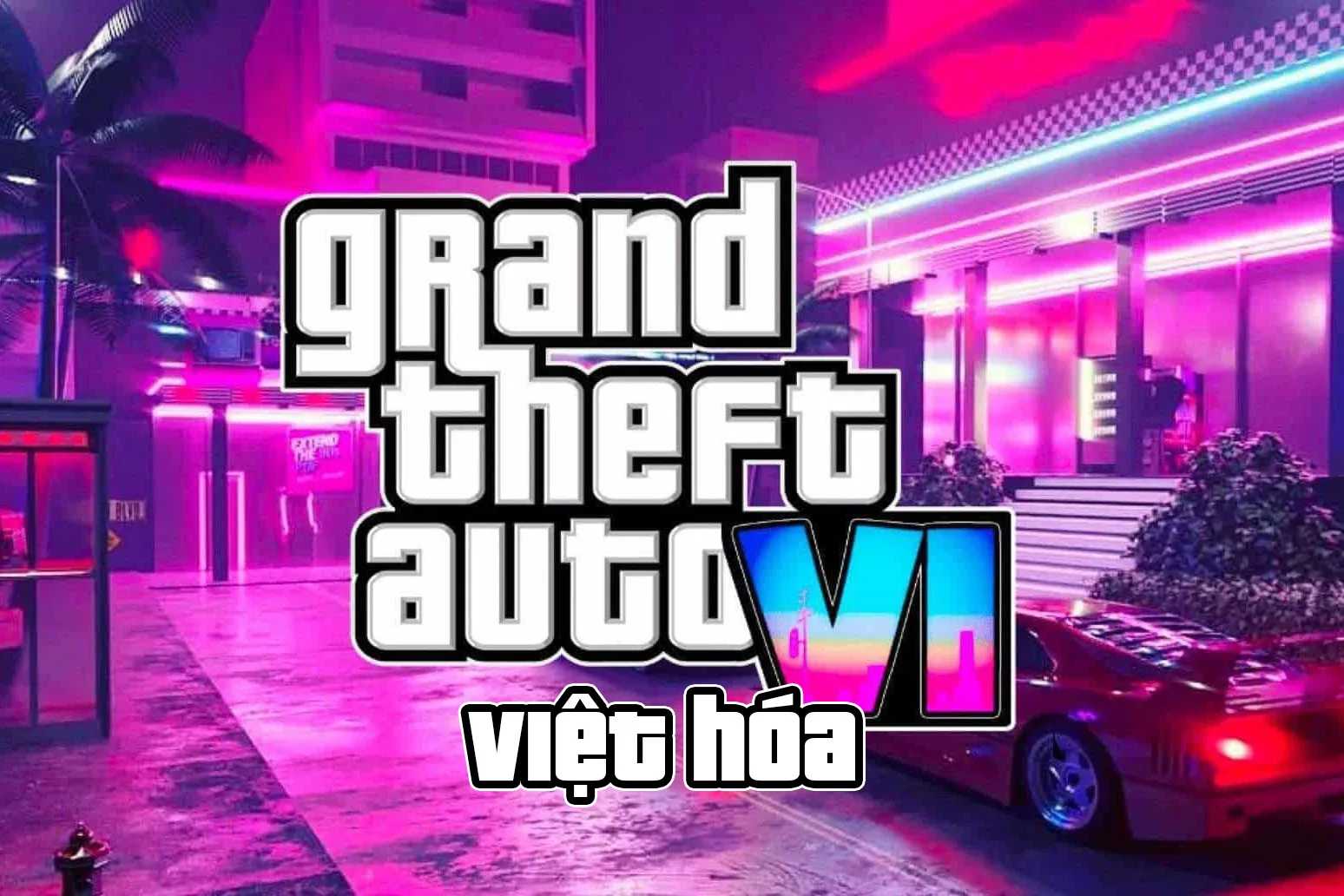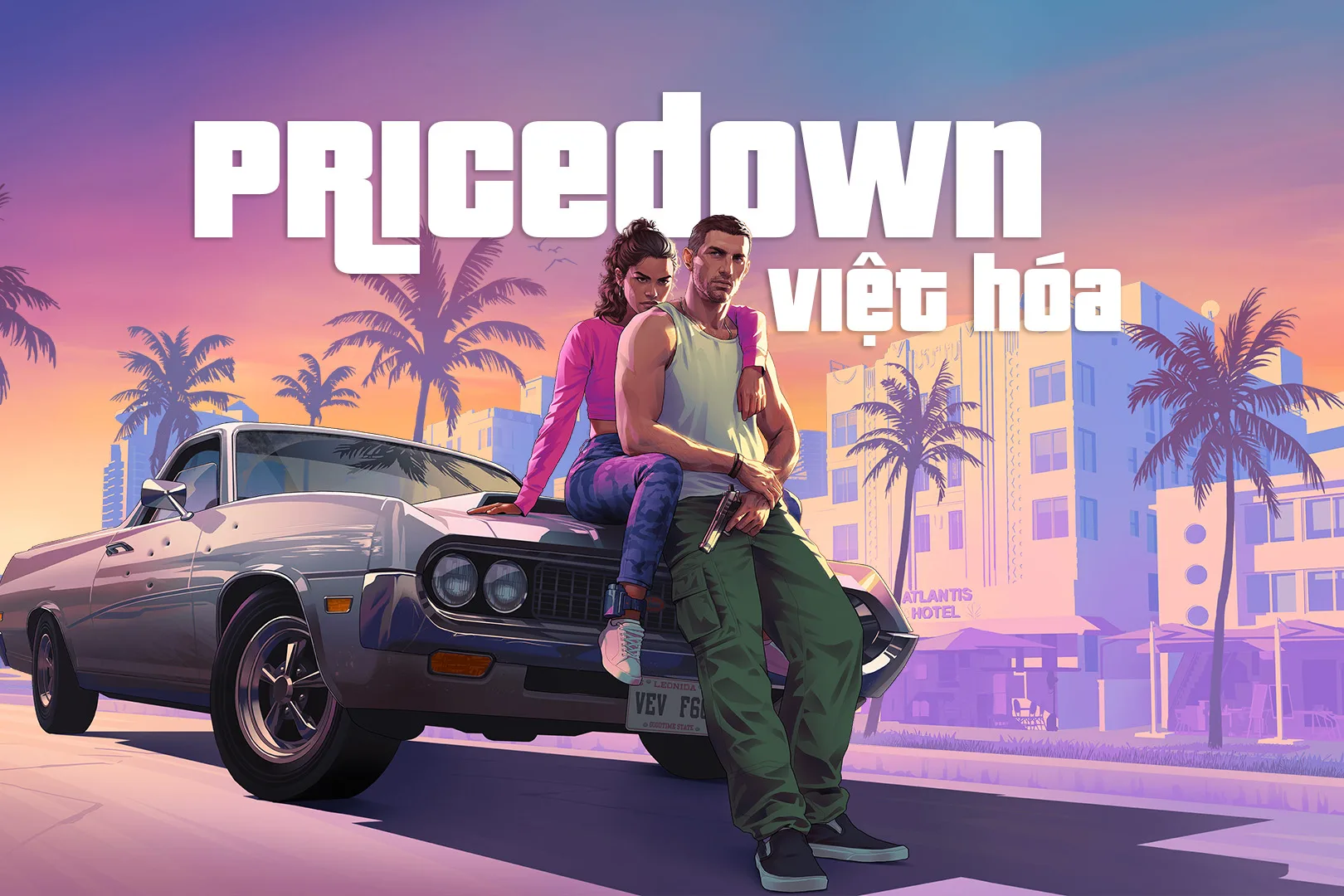
DVN Pricedown Việt hóa – Font chữ Game GTA quen thuộc
DVN Pricedown là một Display Typeface mang đậm ngôn ngữ thiết kế của các tựa game retro, tái hiện xuất sắc phong cách thị giác từ logo đặc trưng của chuỗi game Grand Theft Auto (GTA). Font chữ gây ấn tượng mạnh với khối lượng chữ (mass) lớn, trọng lượng nét cực dày và thiết lập khoảng cách ký tự (tracking/kerning) được ép sát tối đa. Đặc điểm nhận diện cốt lõi nằm ở cấu trúc hình học phá cách, nơi các nét đứng (stem) và chân chữ của một số ký tự được kéo dài có chủ đích vượt khỏi đường baseline hoặc cap height, tạo ra hiệu ứng lồng ghép thị giác liền mạch, góc cạnh và mang đậm hơi thở đường phố.
Về mặt kỹ thuật, hệ thống dấu thanh tiếng Việt đã được tinh chỉnh khắt khe về tỷ lệ và vị trí (positioning) để đồng bộ hoàn toàn với độ dày nét nguyên bản. Sự tối ưu này triệt tiêu tình trạng gãy cấu trúc hay dính nét (overlap) khi gõ các cụm từ tiếng Việt phức tạp ở kích thước lớn. Với DNA thiết kế mang tính biểu tượng, DVN Pricedown là giải pháp kỹ thuật tối ưu cho các tác vụ hiển thị yêu cầu độ nhấn mạnh cao như thiết kế logo game, typography, poster, banner sự kiện eSports hoặc đồ họa giao diện streaming.